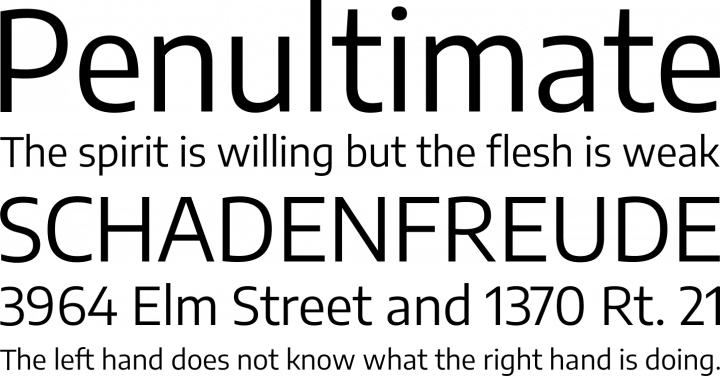
Alternativen zur Encode Sans mit kyrillischem Zeichensatz?
habt Ihr spontan einen Vorschlag, welche Fontfamilie als Alternative zur Encode Sans – also eckig ausgespannt – passend könnte und dabei einen kyrillischen Zeichensatz bietet? Fünf Weiten wie bei der Encode müssen nicht unbedingt enthalten sein, aber eine zweite, schmallaufende wäre gut.
Beispiel Encode Sans, Quelle: fontsquirrel.com
Allerdings sehe ich nicht, dass sie kyrillisch kann
Ich wollte mich erstmal vergewissern, dass ich die Form einigermaßen vertstanden hab ...
Wie wär's denn mit der Neo Sans? Obwohl es die auch schon wieder nicht gequetscht gibt – ist doch immer irgendwas ;-)
PS: Alternativen ???
Wie wär's denn mit der Neo Sans?
Wie hast Du das kyrillische Alphabet entdeckt? Im Grunde okay aber ohne rundgelutschte Strichenden (ähnlich Square Sans) wäre sie mir lieber. Die Soho Gothic von Sebastian Lester kann nicht etwa auch kyrillisch, oder? Die wäre optimaler, aber in der Glyphentabelle bei Myfonts spricht sie kein russisch. :shock:
N.b. Die Exo (1) hat ein zweistöckiges Alternativ-g (nur eben kein Kyrillisch). Falls es nur um ein Logo o.ä. gehen sollte, könnte man vielleicht basteln. :-?
Wie hast Du das kyrillische Alphabet entdeckt?
Einfach eine Handvoll Unicode-Kyrillisch in das Mustertextfeld bei Myfonts eingegeben – und dann gucken, wo's funktioniert ;-)
Bei der Soho Gothic funktioniert's nicht:
Einfach eine Handvoll Unicode-Kyrillisch in das Mustertextfeld bei Myfonts eingegeben – und dann gucken, wo's funktioniert ;-)
Bei der Soho Gothic funktioniert's nicht:
Dank Dir! Die sind wie die Rogan weitestgehend ziemlich geschlossen – was mich nicht stört und ich in jedem Fall mit vorschlagen werde. Aber evtl. den Auftraggeber, da er durch die Encode die eher offenere Struktur gewöhnt ist. Falls Dir also noch etwas offeneres einfällt … ;-)
;-) Ja. Über diesen Weg bin ich zu den  oben genannten Fundstücken gekommen. Und bei Google und Fontstand gibt es ähnliche Filteroptionen. Typekit habe ich auch durch. Dort war aber überall nichts dabei, was mich überzeugt hat.
Kostengünstige:
Fira Sans von Erik Spiekermann und Ralph du Carrois
PT Sans von Paratype
Open Sans von Steve Matteson
Noto Sans von Monotype
Glober von Fontfabric
M+1 von M+Fonts
Kommerzielle
Graublau Sans von Georg Seifert:-P
Cyntho Pro von Minttype
Cormac von Typedepot
Fedra Sans von Typotheque
Mayberry Pro von Steve Matteson
Droid Sans von Steve Matteson